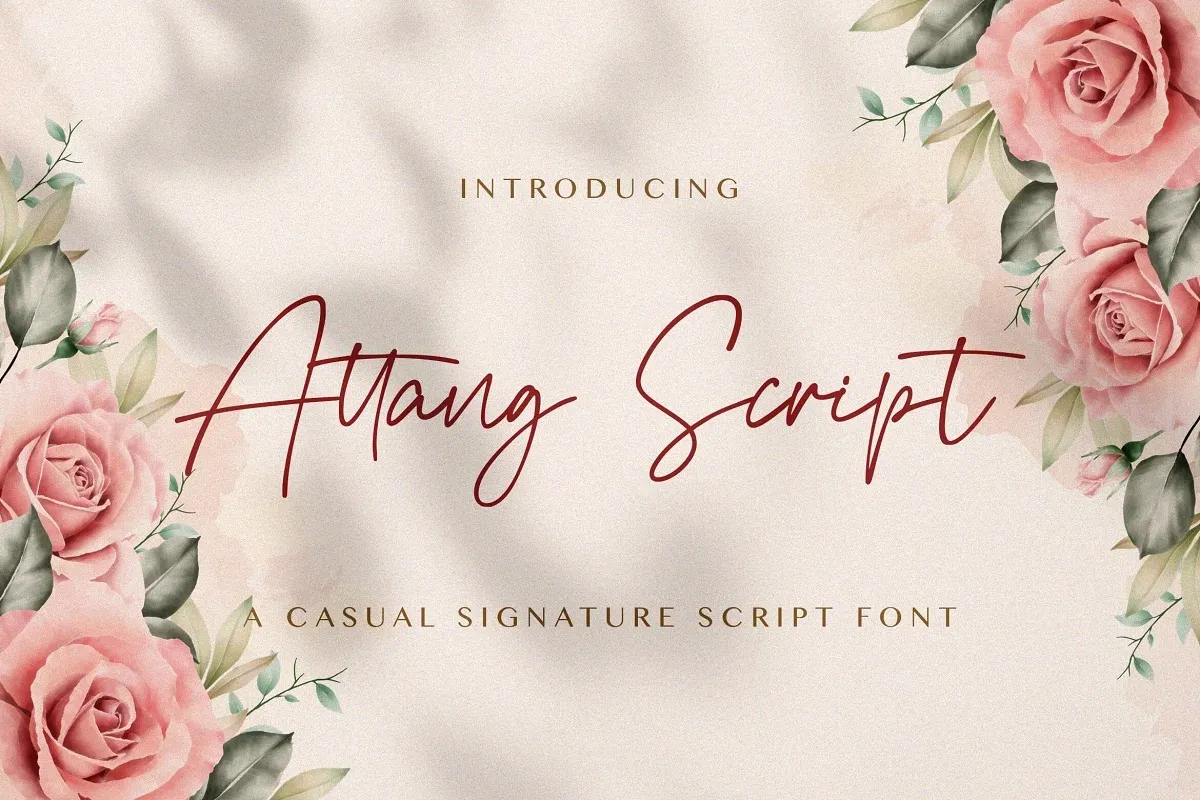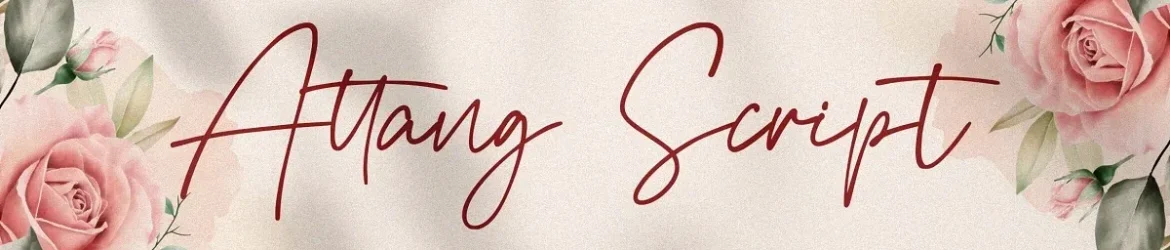
Attang Script Font – Download Grátis
Esta é uma tipografia script levemente desencontrada criada pelo designer StringLabs. As letras são únicas e têm um toque brincalhão e arredondado, com caracteres belos e bem equilibrados que lhe permitem se adaptar a uma ampla variedade de designs. Experimente adicioná-la às suas propostas mais audaciosas e observe como ela transforma esses projetos em algo realmente viva e interessante. A fonte Attang Script é perfeita para criar design criativo e divertido, seja para anúncios, cartões ou qualquer projeto onde você deseja chamar a atenção do seu público-alvo com uma escrita única e impactante.